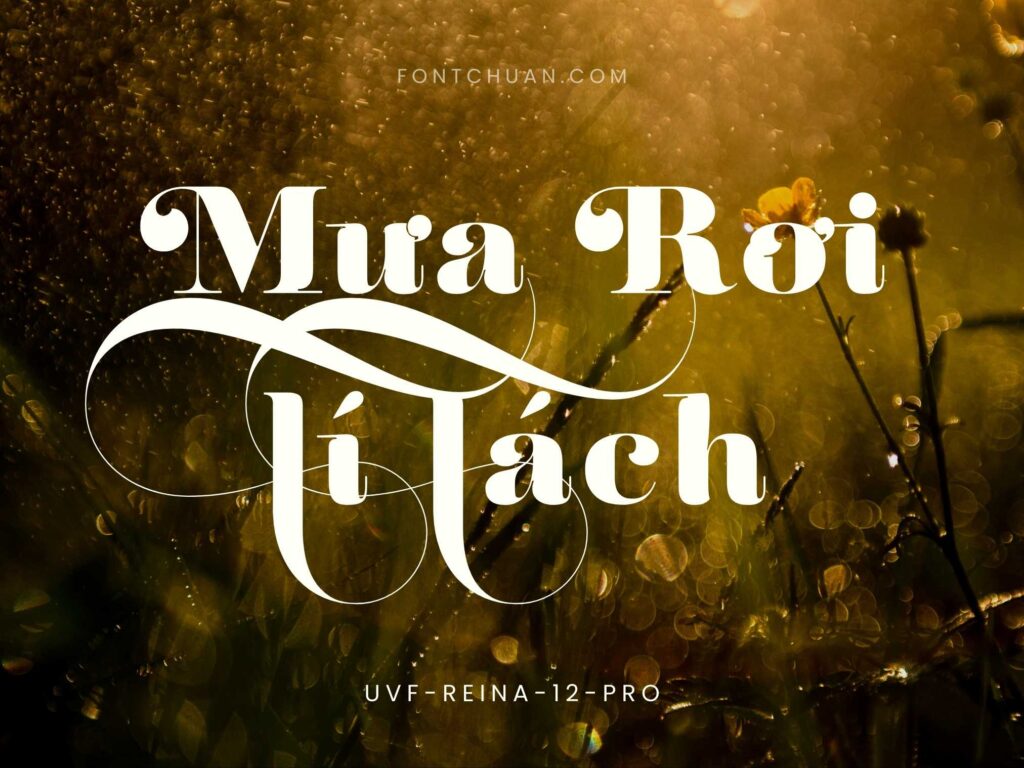
Font UVF Reina 12 Pro Việt Hóa
Reina 12 Pro là một kiểu chữ serif trang trí được thiết kế bởi Maximiliano R. Sproviero. Font này nổi bật với các đường nét đậm và sự tương phản cao giữa các nét dày và mỏng, tạo nên vẻ đẹp sang trọng và tinh tế. Với các chi tiết trang trí độc đáo, Reina 12 Pro mang lại cảm giác cổ điển nhưng không kém phần hiện đại, phù hợp cho các dự án thiết kế cần sự thu hút và ấn tượng.
Font này đã được Việt hóa, hỗ trợ đầy đủ các ký tự tiếng Việt, giúp người dùng tại Việt Nam dễ dàng sử dụng trong các dự án của mình. Reina 12 Pro phù hợp cho các ứng dụng như thiết kế logo, tiêu đề, thiệp mời và các ấn phẩm nghệ thuật. Trong lĩnh vực sự kiện, font này có thể được sử dụng trong các dịp như lễ hội, lễ cưới và các sự kiện văn hóa. Ngoài ra, Reina 12 Pro cũng thích hợp cho các ngành nghề như thiết kế đồ họa, nghệ thuật trang trí và xuất bản.